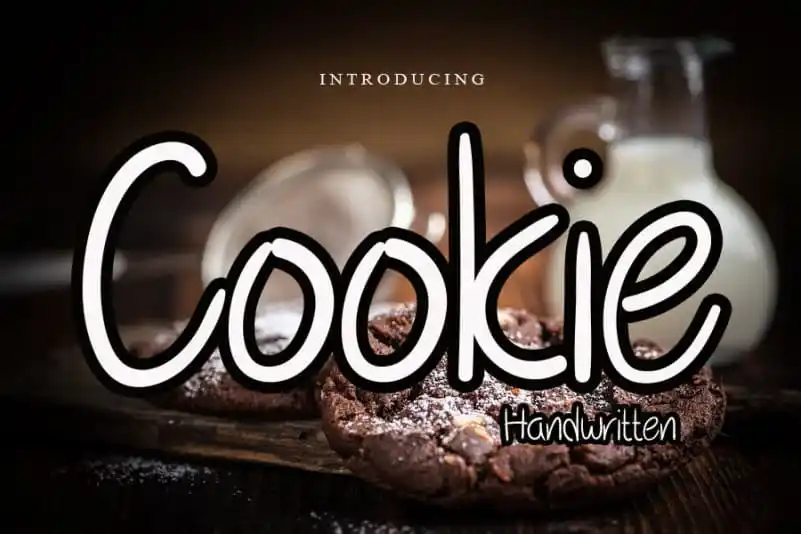
Cookie Display Font – Download Grátis
A Cookie Display Font é uma elegante fonte escrita à mão que possui características suaves e flexíveis. Seu estilo carinhosamente simples e alegre torna-a perfeita para transformar qualquer projeto em obras de arte, seja ela um logotipo, um título ou até mesmo conteúdo editorial. Esta fonte traz uma pitada de doces nuances ao seu trabalho, adicionando um toque suave que vai do básico ao chamativo com facilidade. Sua versatilidade e flexibilidade fazem dela uma escolha ideal para designers criativos e amantes de detalhes que buscam expressar suas ideias de maneira única e encantadora. Com a Cookie Display Font, você pode explorar infinitas combinações e variações, garantindo sempre um resultado especial e memorável. Descubra o prazer desta fonte maravilhosa e faça dela uma parte essencial do seu design digital.